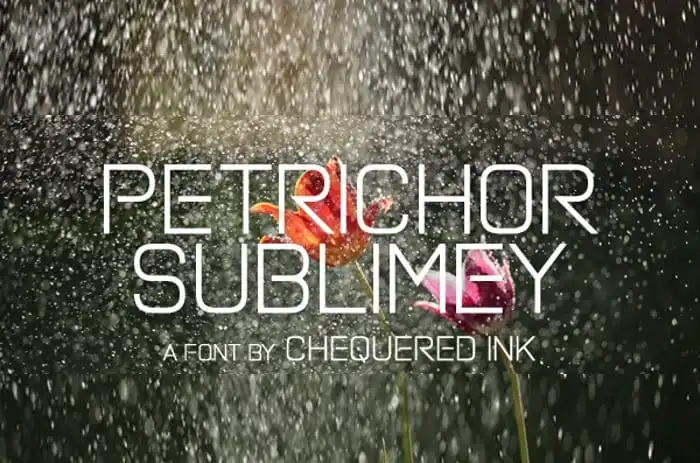
A Petrichor Sublimey Display Font é uma elegante tipografia sem serif de destaque que traz modernidade para qualquer projeto visual. Confeccionada para complementar tanto capas de revistas, títulos e artigos na web quanto cartões profissionais, embalagens de produtos ou até mesmo capas de álbuns, esta fonte combina facilidade de leitura com um toque sofisticado. Perfeito para transmitir uma mensagem clara e moderna em um design amplo, a Petrichor Sublimey Display é perfeita tanto para grandes títulos quanto para textos menores, garantindo que o seu projeto seja chamativo e profissional de início a fim. Essa fonte se destaca como uma opção versátil e elegante no mundo das fuentes sem serif.